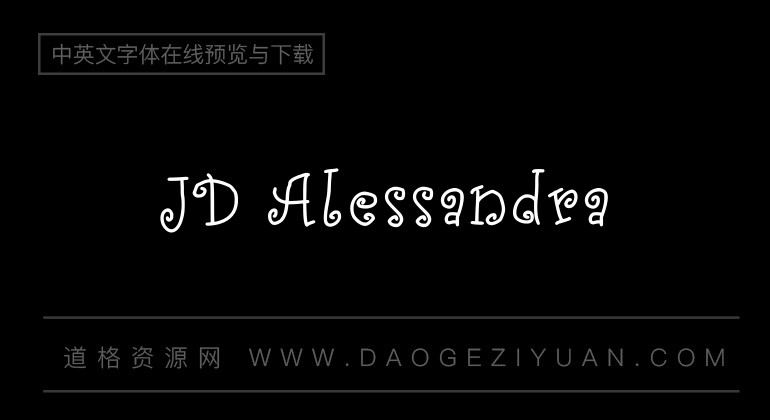
JD Alessandra是一款由Juanjo López de la Cruz开发的现代字体,它具有简洁而又引人入胜的外观。它的设计风格灵感来自于罗马文字和古典文字,结合了现代元素,使其具有现代感。它的字体结构紧凑,具有良好的可读性,适合用于印刷、网络和其他媒体。JD Alessandra字体支持多种字形,可以满足不同的设计需求。内容介绍
JD Alessandra是一款非常不错的手写艺术字体,具有很好的视觉感,适合于文化类的宣传设计、商业类品牌的广告和产品包装设计以及个性化文字排版等较多场景。